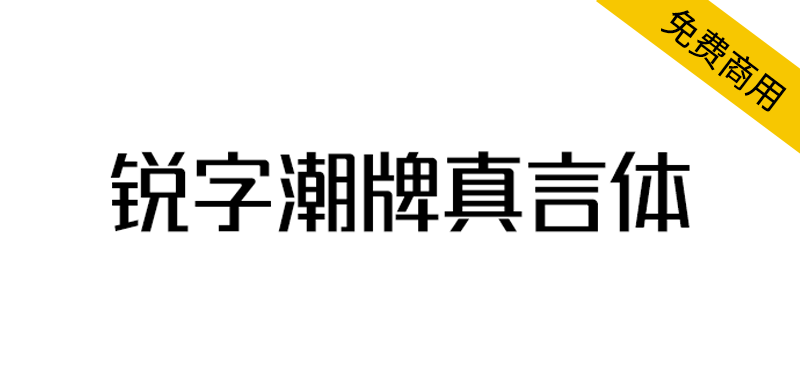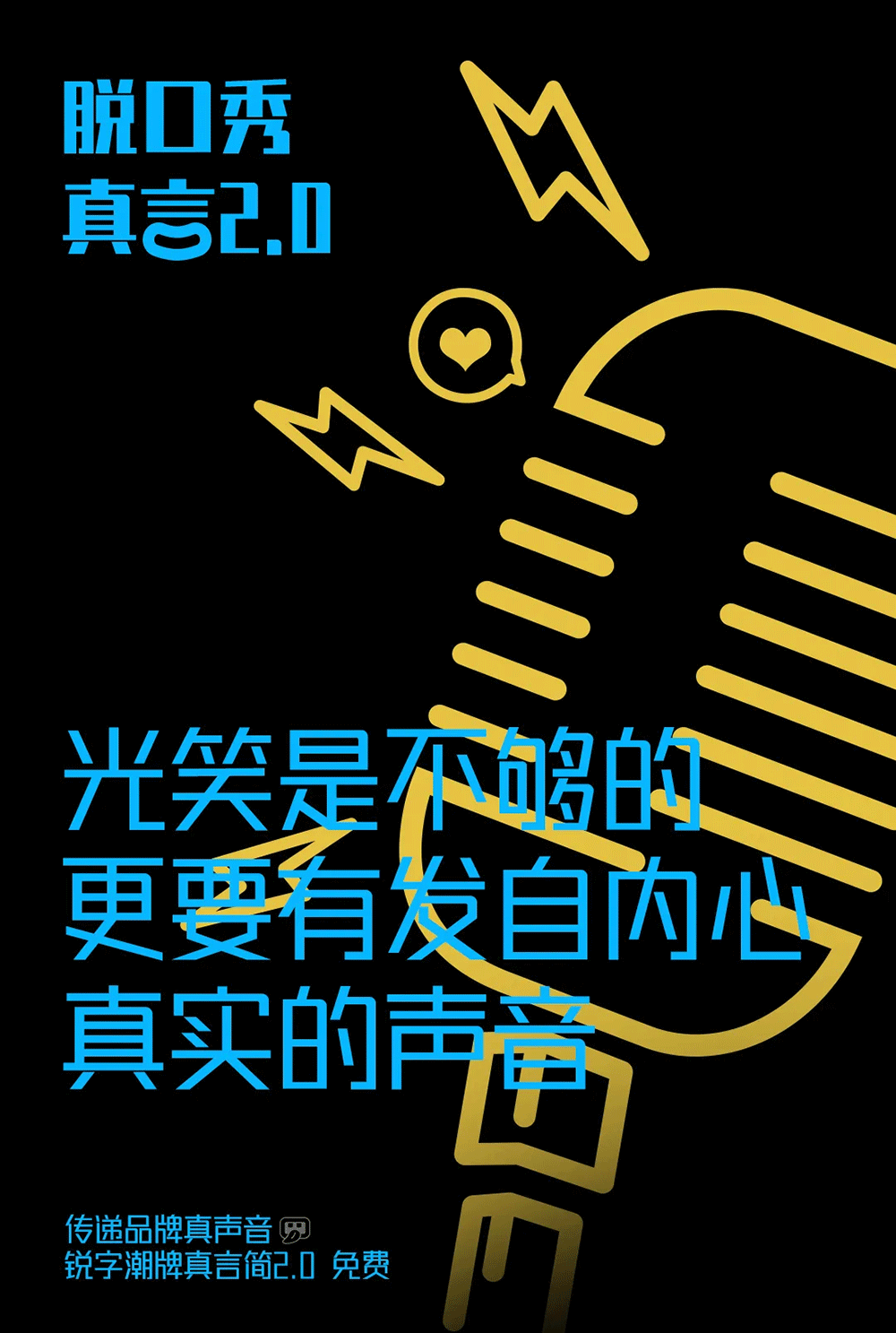
锐字潮牌字库成立7周年重磅官宣:锐字潮牌真言简2.0全新升级发布!免费商用!本次升级调整字体结构;新增6个字重;增加17个繁体与生僻的常用字,共7672个字符。并支持可变字体!可随心所欲自由变换,把字体玩出花!现面向社会开放下载,
品牌真言,即品牌灵魂。锐字潮牌真言简2.0免费,在1.0版本基础上进行视觉升级,全方位展现品牌信息,更好地传递品牌真声音。
更具呼吸感、通用性更强:锐字潮牌真言简2.0细体文字,结构干净,笔画移除了粗细对比,因此辨识度更高,字形看起来更加清晰、干净。中性的笔画设计与分隔使得细体文字通用性更强,排版也更有质感,画面看上去更加轻盈,具有呼吸感,更容易阅读。